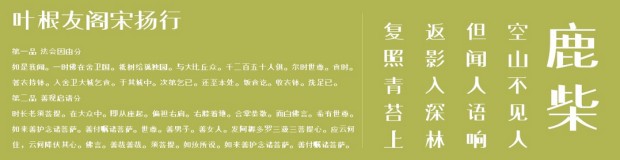
葉根友閣宋揚(yáng)行體
葉根友閣宋揚(yáng)行是葉根友閣宋字體系列中用途非常廣泛的字體了,這款字體非常美化,并且適用于各種場(chǎng)合,有需要的就來(lái)下載吧!
葉根友閣宋揚(yáng)行字體是一款用廣告海報(bào)設(shè)計(jì)方面的字體,這款字體是以葉根友字體為原型所創(chuàng)作出的字體,結(jié)體寬綽秀美,整體字形筆畫均衡,風(fēng)格現(xiàn)代,字體端正易認(rèn)。此款字體適用于創(chuàng)意設(shè)計(jì)、藝術(shù)設(shè)計(jì)、書寫設(shè)計(jì)等方面,需要的話可以來(lái)下載使用。
葉根友閣宋揚(yáng)行體,非常秀美,并且每一筆每一劃店都是均衡而且英文字形也漂亮哦!